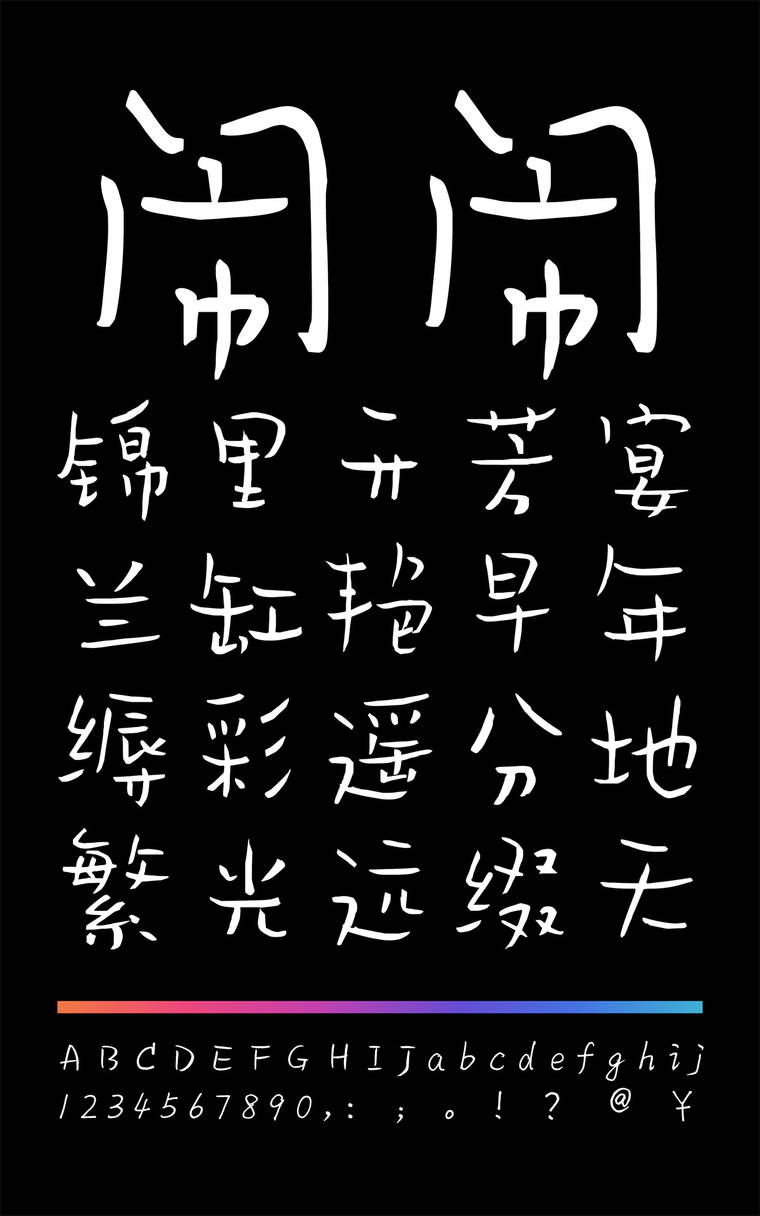
小豆岛闹闹体简
小豆岛闹闹体简,这款字体结构工整、笔画清晰,兼顾美观与易读性,适用于标题、正文、海报、包装、LOGO 等多种场景。字形优雅稳定,风格百搭耐看,适配日常排版与创意设计,让文字呈现更舒适、更具质感。小豆岛闹闹体简一笔一画,皆是细节,以均衡的比例、流畅的线条打造舒适视觉体验,字形端正大气,风格简约现代。无论是商业设计、品牌宣传还是日常排版,都能轻松驾驭,让文字更有格调与力量。小豆岛闹闹体简字体下载。
字体特征:小豆岛闹闹体笔触轻快随性,笔画轻重有度,字形灵动,形散神聚,落笔急促个性,整体给人以活泼跳跃的感觉,趣味十足,不对称的字体形态在视觉上给人轻松感,极具手写字体的个性风。字体整体风格统一,应用性强,可以拉伸使用,线条富有节奏与灵气,灰度均匀。